Poster design করার সময় font নির্বাচন প্রয়োজন যেমন Visual impact, readability, আর personality। নিচের ফন্টগুলো প্রায় সবাই poster, banner, thumbnail design-এ ব্যবহার করে থাকে। প্রতিটা font-এর নিচে আমি short review, usage idea এবং author link দিলাম।
1. Mahfuj Megna Version2
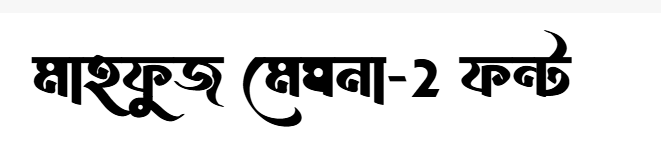
Designer: এইচ এম মাহফুজ
Mahfuj Megna একটি bold এবং stylish Bangla font যা poster design-এ আকর্ষণ তৈরি করে। এই ফন্টের ক্যারেক্টারগুলো traditional Bangla look ধরে রাখলেও modern edge আছে, তাই headings এবং short text-এ দারুন দেখা যায়।
দ্বিতীয় স্টাইলটি একটু heavier এবং display purpose-এ আরও ভালো।
এই ফন্ট poster headline, event title, এবং notice board design-এ খুব ভালো লেগে থাকে।
2. ChhatrishJuly Font
ChhatrishJuly একটি classic calligraphy-touch Bangla font, যেটা traditional poster work-এ দারুন appeal তৈরি করে। এই ফন্টে আছে smooth strokes এবং elegant curves, তাই cultural event posters, invitation visuals এবং social banners-এ এটা eye-catching।
Lipighor-এর ফন্টগুলো অনেক সময় creative community-তে popular হয়, কারণ এগুলো handwritten look ধরে রাখে। Poster design-এ এটা main title হিসেবে ব্যবহার করলে খুব ভালো results আসে।
3. Aboroni Unicode
Aboroni Unicode একপঙ্খ bold Bengali font। Poster design-এ যখন contrast দরকার, তখন এটি headline-এ strong visual punch দেয়। Unicode হওয়ায় এটি সব device এবং software-এ smooth support করে।
Typography-based posters-এ এই ফন্ট high readability দেয়, তাই short and medium text-এ এমনিতেই ভালো লাগে।
4. Jannatul Ferdous Stylish Font
Designer: (via FontLipi)
Jannatul Ferdous একটি expressive stylish font, যার strokes একটু playful এবং creative design-এ ভালো। Social media poster কাজ, art themed visuals বা creative portfolio poster-এ এটি জিনিসটাকে alive লাগাতে সাহায্য করে।
Headline বা strapline-এ use করলে এটা attention grip করে, আর subtitling-এ use করলে contrast আসে।
5. Sohid Osman Hadi Font
Sohid Osman Hadi একটি clean and balanced free Bangla font। Poster-এ যারা readable, professional look চান, তাদের জন্য এটি একটি strong choice। Style এতটা decorative না হলেও headline বা tagline-এ use করলে readable এবং professional output দেয়।
6. HasanHera Font
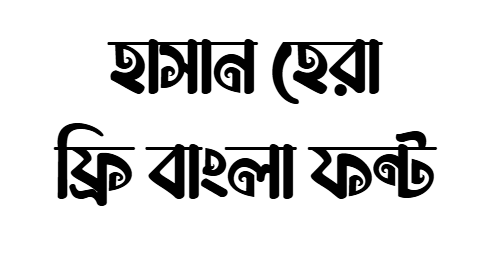
HasanHera একটি elegant Bangla font যা display poster design-এ ব্যবহার করা যায়, বিশেষ করে cultural festival, quotes poster বা typography poster-এ। এই font এর soft curves এবং balanced shape design-এ subtle impact দেয়।
প্রায় classic look দেয়, তাই minimalist poster design-এও ভালো কাজ করে।
7. Mahin Dui Dashok
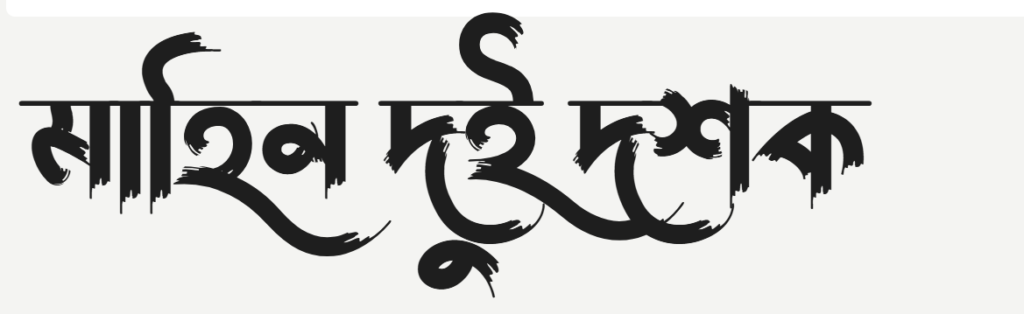
Mahin Dui Dashok একটি fairly bold font। Poster work-এর জন্য large text support করে আর spacing ঠিক রাখা হয়েছে, যেটা poster typography-এর জন্য গুরুত্বপূর্ণ। Event details, dates, or main text blocks-এ এটি readable output দেয়।
8. Abu Sayed Font
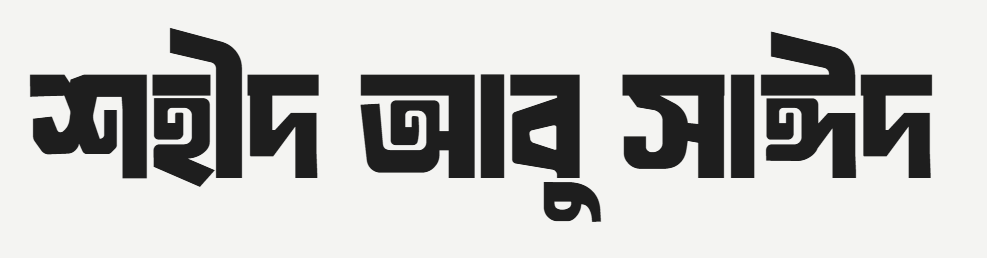
Abu Sayed free fontটি classic style রাখে, poster headline বা subtitle হিসেবে ব্যবহার করলে এটা neutral readable look দেয়। Poster design-এ যদি আপনি extreme decorative না চাইলে, এই font একটি safe pick।
Conclusion
২০২৬ সালের জন্য Best Bangla Fonts for Poster Design হিসেবে এসব font ডিজাইনারদের কাছে জনপ্রিয় এবং practical।
যদি আপনি headline-centric, high-impact poster বানাতে চান, তাহলে Mahfuj Megna Version2 এবং Rasule Arabi খুব ভালো choices।
আর যারা subtle, elegant look চান, তাদের জন্য Aboroni Unicode ও Mahin Dui Dashok |